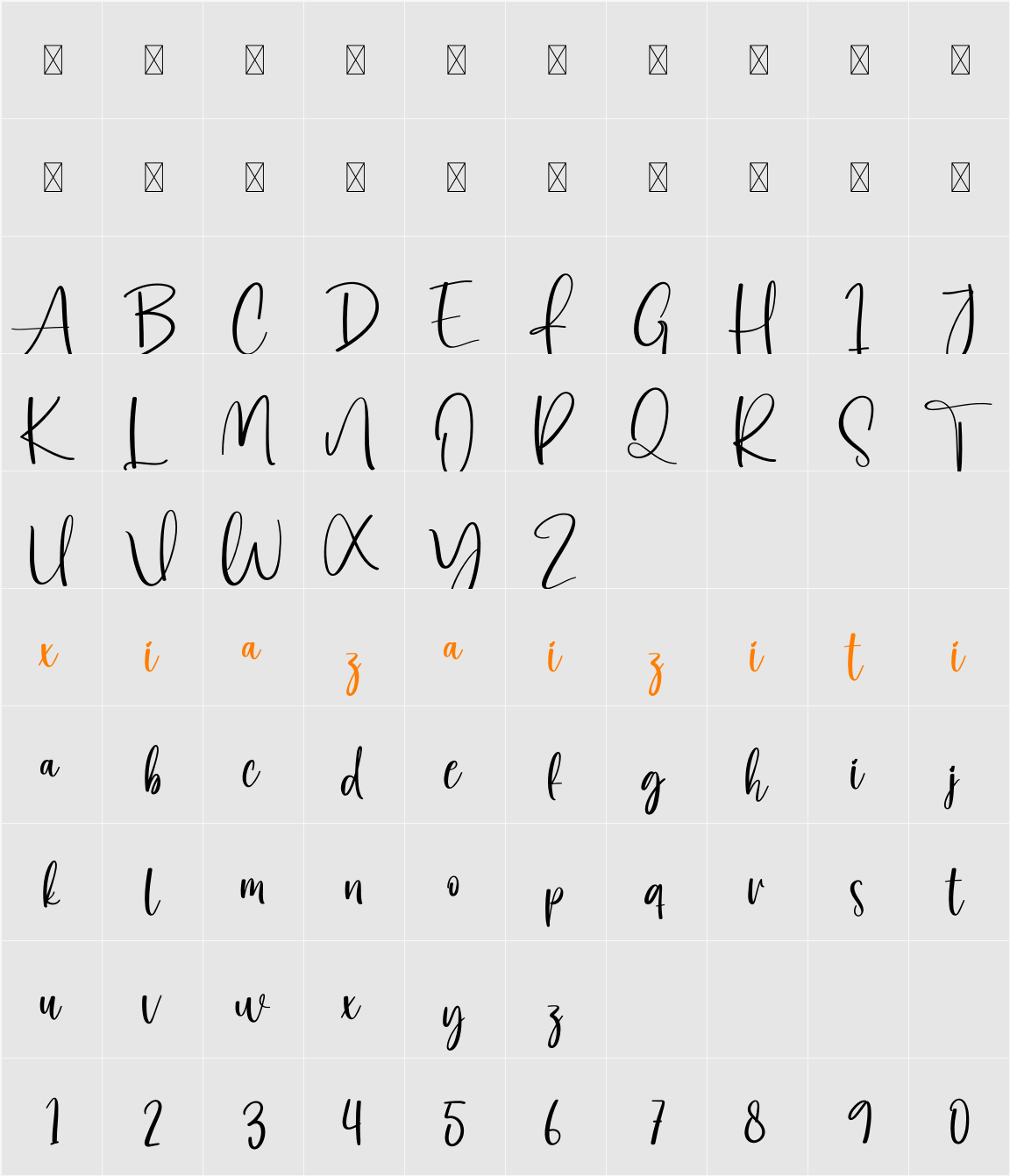
Writing
Writing,这款字体结构工整、笔画清晰,兼顾美观与易读性,适用于标题、正文、海报、包装、LOGO 等多种场景。字形优雅稳定,风格百搭耐看,适配日常排版与创意设计,让文字呈现更舒适、更具质感。Writing一笔一画,皆是细节,以均衡的比例、流畅的线条打造舒适视觉体验,字形端正大气,风格简约现代。无论是商业设计、品牌宣传还是日常排版,都能轻松驾驭,让文字更有格调与力量。Writing字体下载。